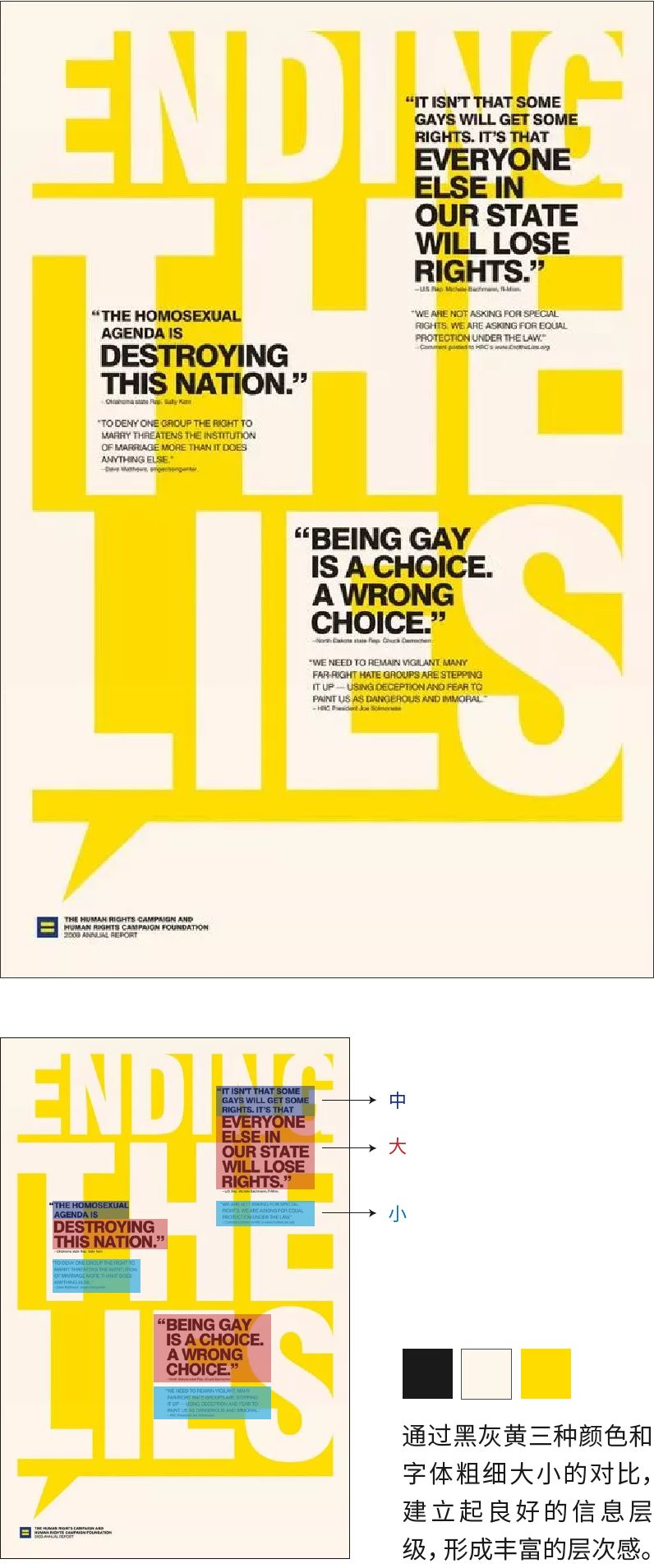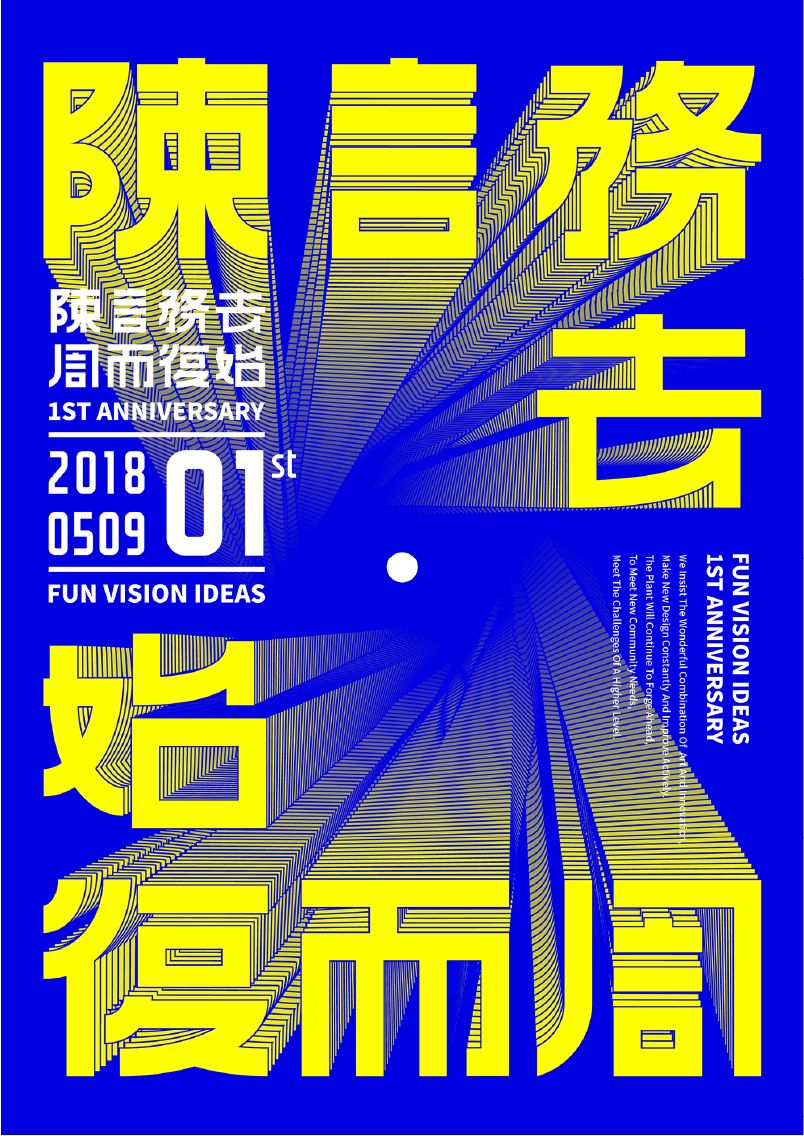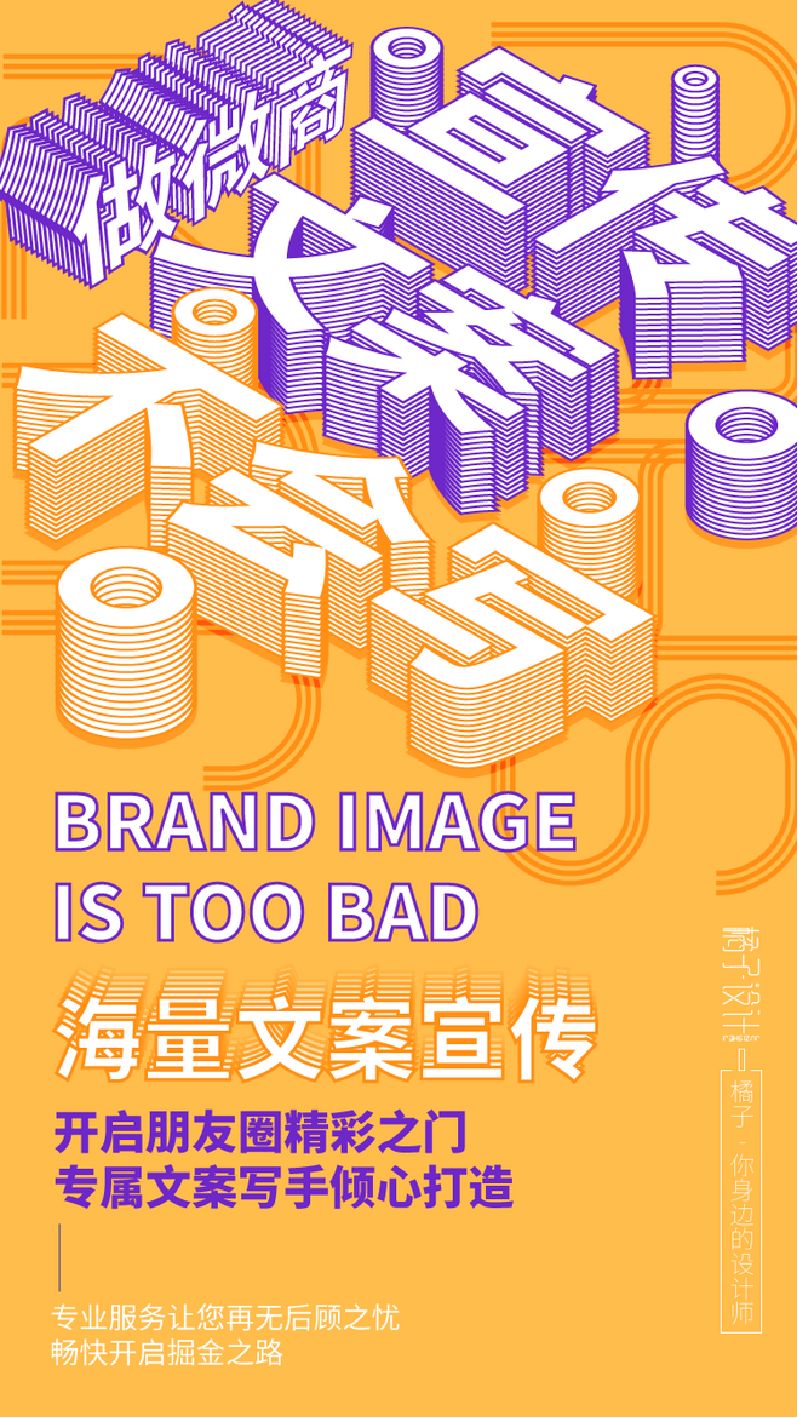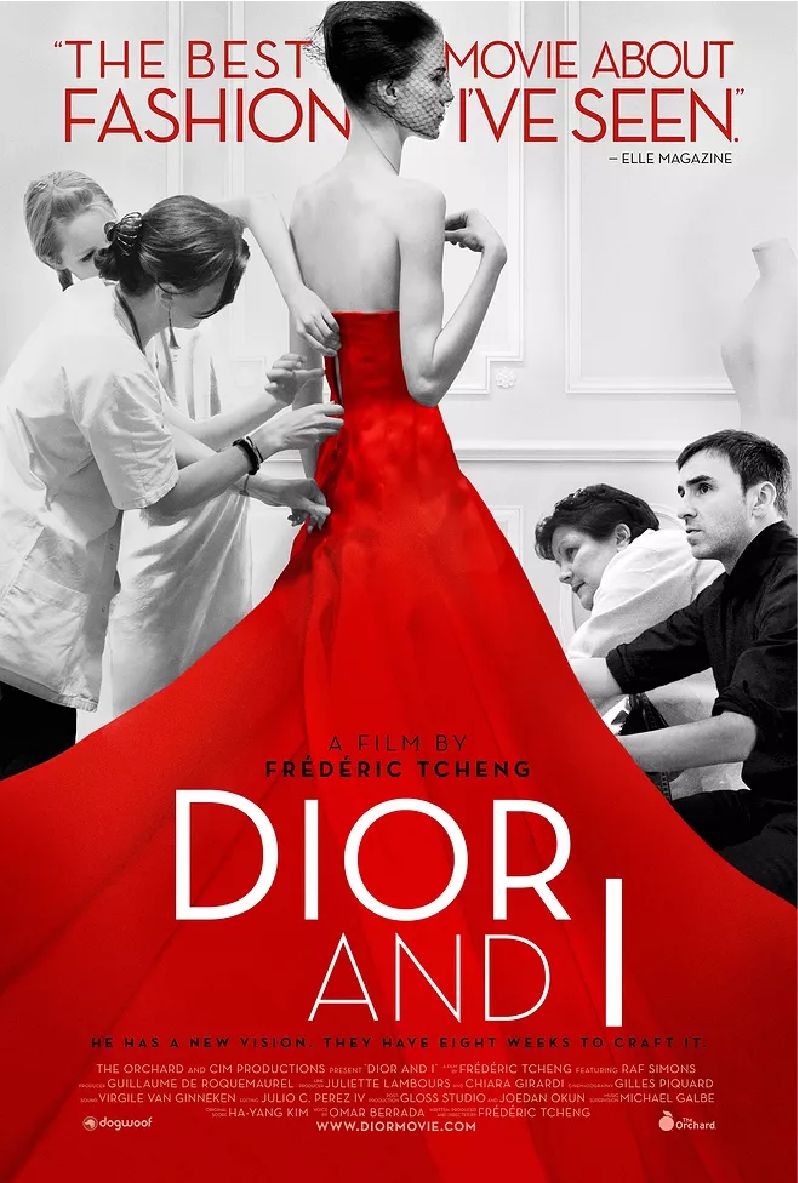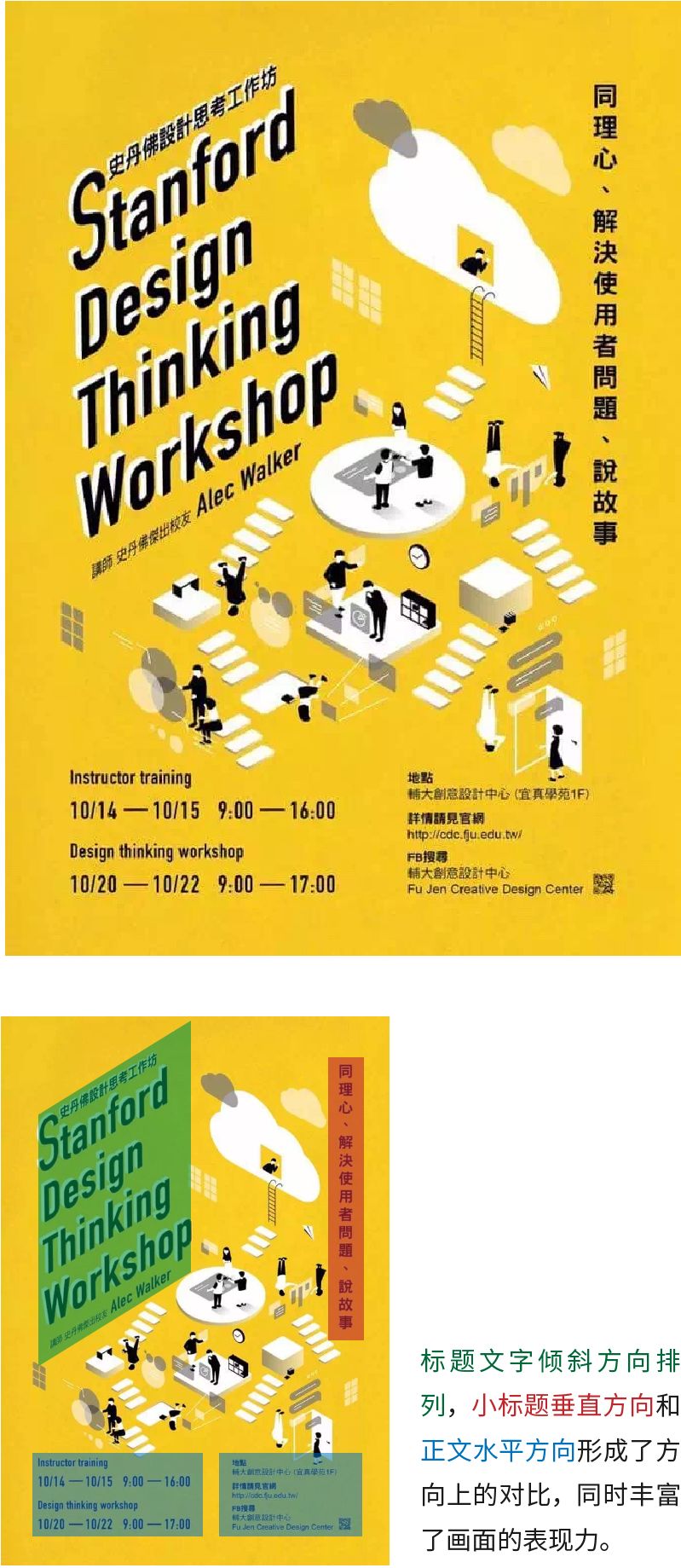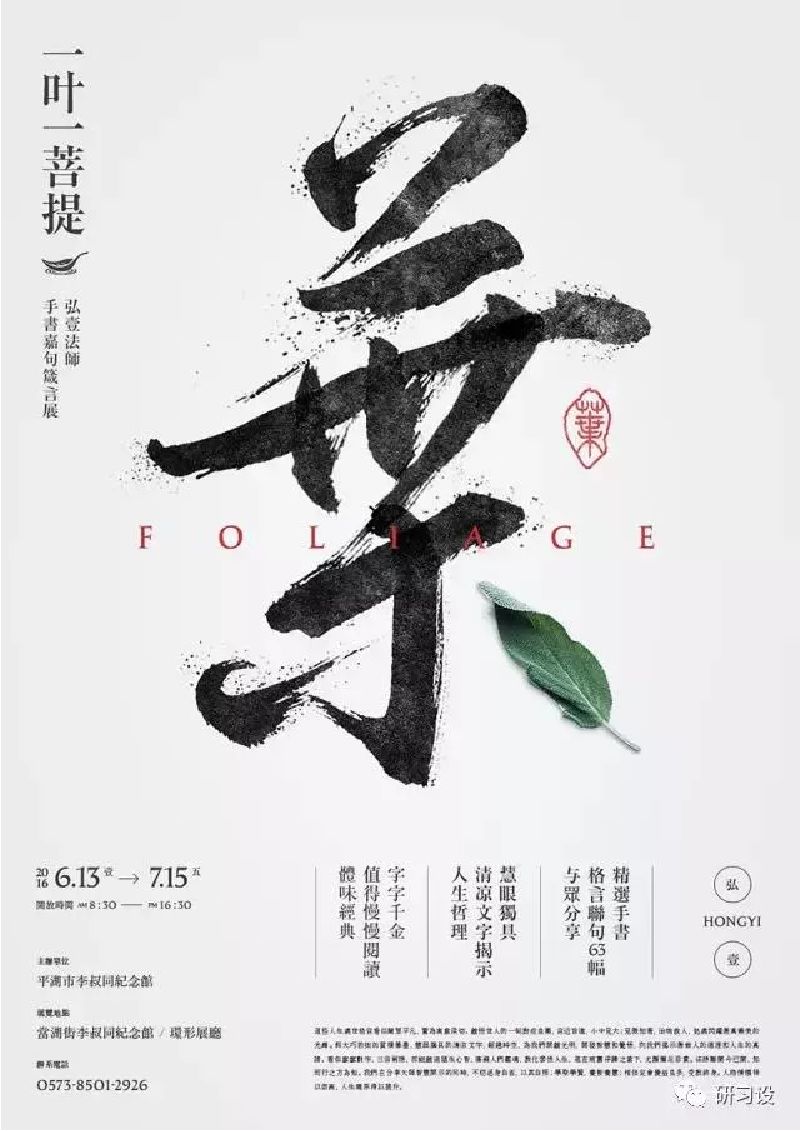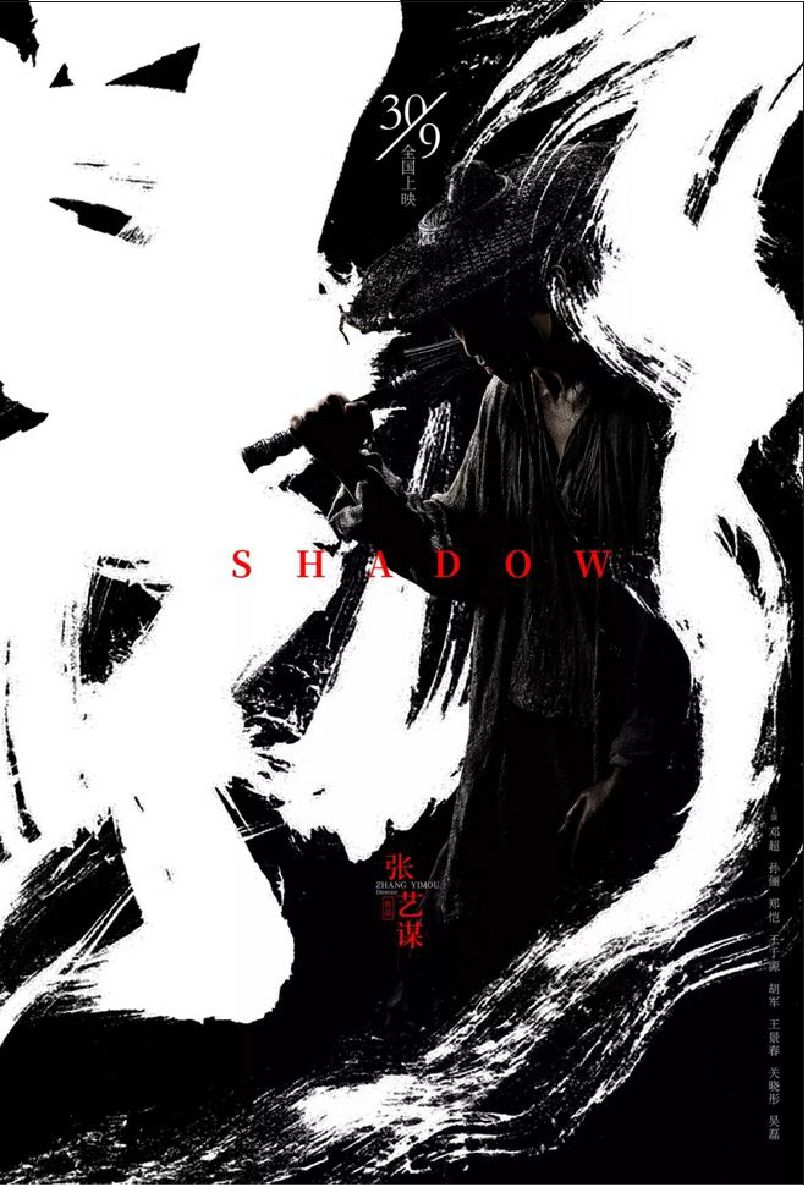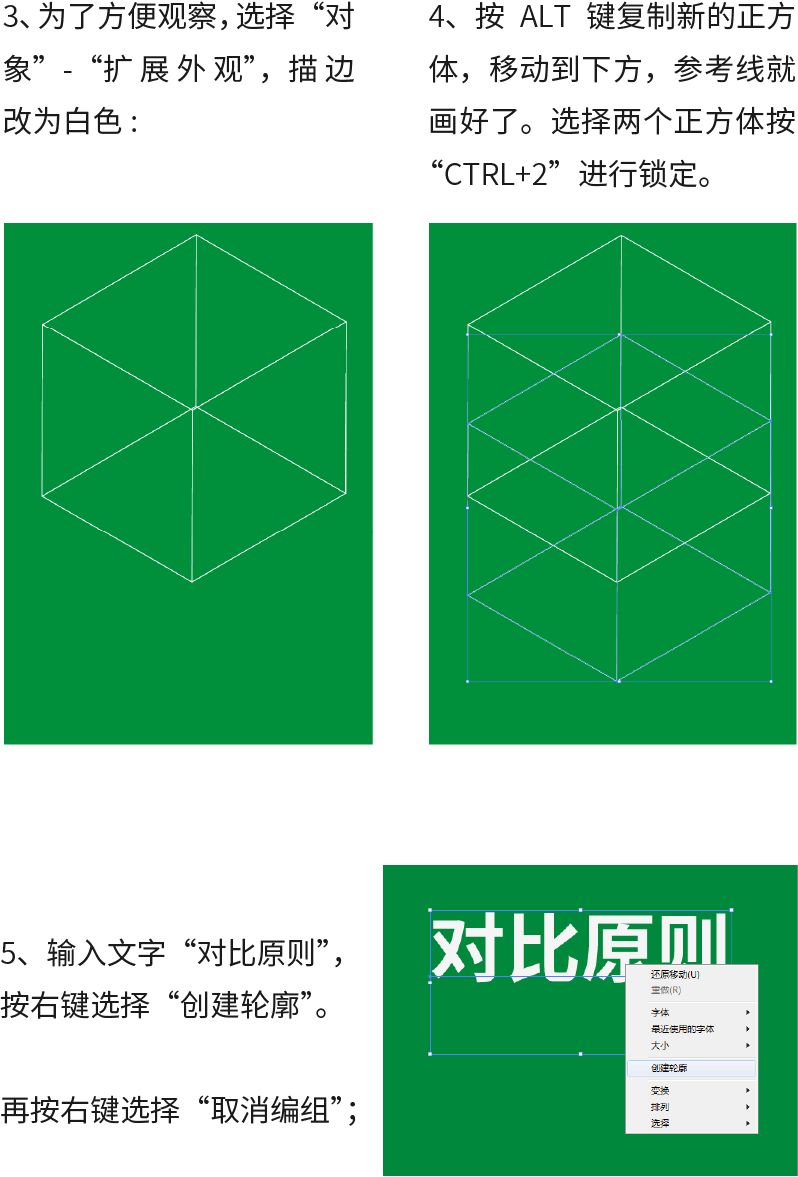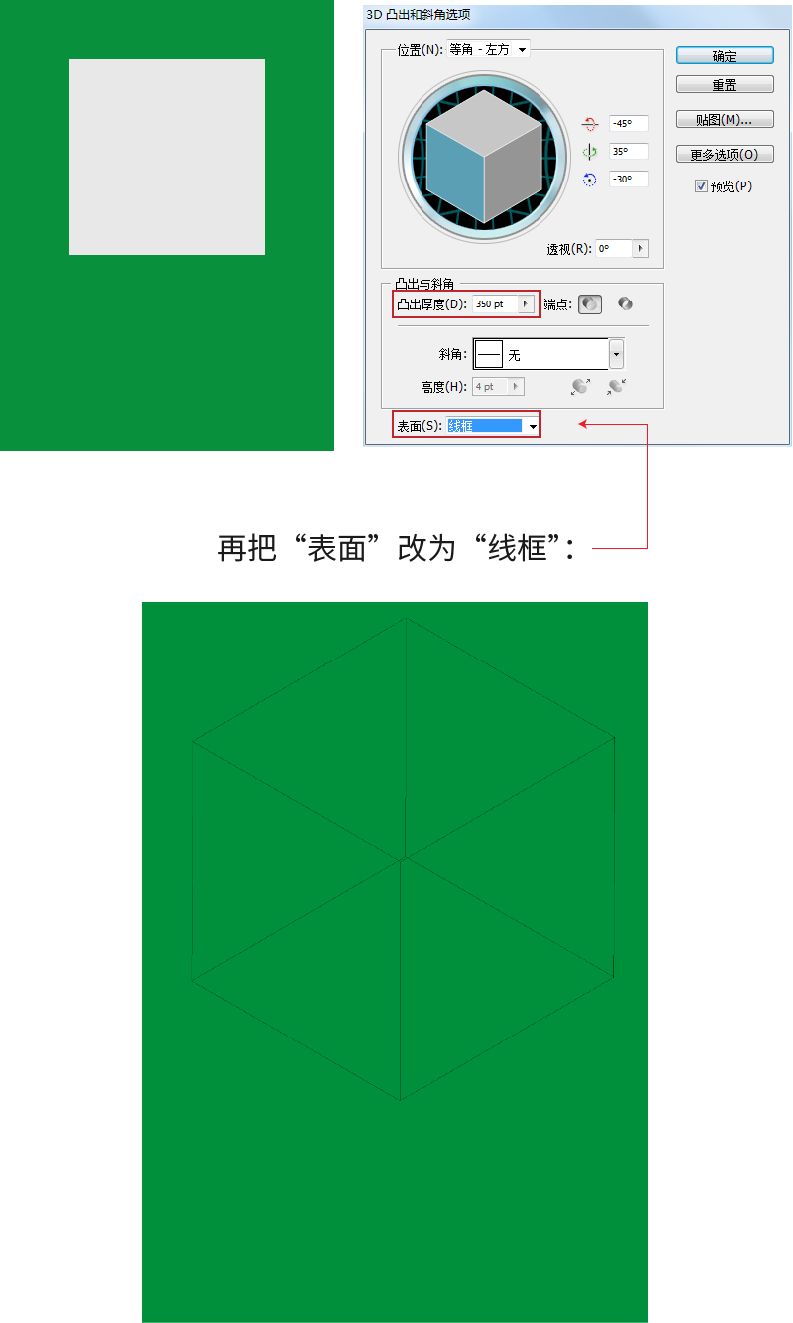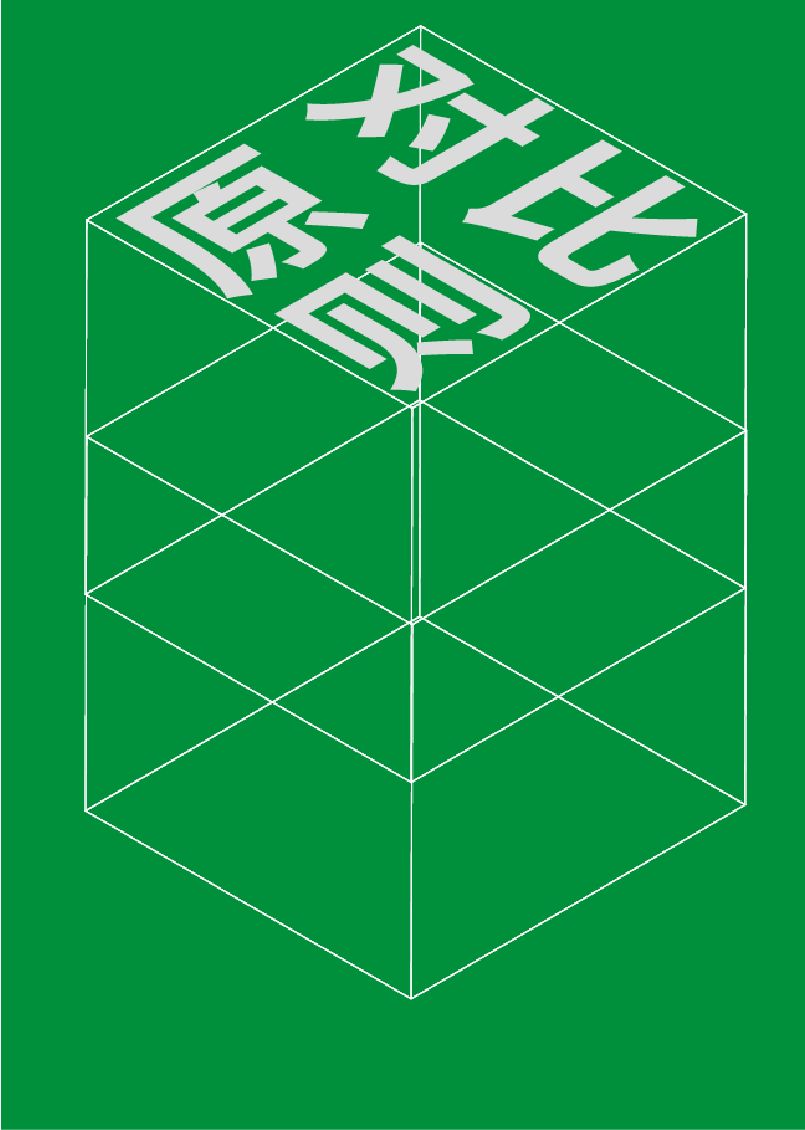
画面太“平”?教你用对比原则解决
重复、对比、对齐以及亲密性是版式设计中的四大原则,各种排版形式与规则都是基于这四大原则衍生而来,而掌握这些具有指导性的设计原则,能够帮助我们在短时间内,更快更好的达成设计目标。本期给大家讲解四大原则之——对比原则。
“对比”强调事物之间的差异性,在设计时要避免页面上的视觉元素太过相似,如果元素之间是为了有所不同,那么加大反差,确保对比是明显并且清晰的。在生活中我们可以随处发现对比的存在,对比形式也是多种多样的:
人们习惯了生活中的对比,如果画面没有对比,会让人感觉很单调乏味。对比可以突出重点,使版面具有层次感,内容要点展示更有条理,对比关系越清晰,视觉效果越强烈。有了对比, 画面才会生动活泼、主次分明。
突出重点
恰当的对比可以很好的制造出焦点(画面主体),在版式编排中,有效利用视觉差异,通过构成要素之间的对比,把读者的注意力吸引到画面的主体部分上来,提高版面的注目效果,是版式设计的重中之重。
利用鲜明的对比,可以形成强有力的反差效果,能第一时间让读者捕捉到主体和重点。此案例主要采用了色彩对比,主体人物和文字在版面中都异常显眼,因为它相比周围的视觉元素产生了很强的差异性。
丰富画面层次
对比是为版面建立有组织的层次结构最有效的方法。强烈的对比可以形成视觉落差,建立良好的信息层次,增强版面的节奏和明快感。
打破呆板、活泼生动
通过对比的形式可以避免版面的单调与平淡,使版面更富趣味性,也使得版面更加鲜活、生动,产生良好的视觉体验,激发读者阅读和观看的兴趣。
用方向、大小和色彩形成对比,使标题与正文的层级更清晰明了,同时加入肌理对比为主体打造立体感,让版面更活泼,更抓人眼球。
理论上元素的一切可改变特征都是可以形成对比,本期只举例了部分常用的文字编排对比形式。
大小对比
通过放大视觉元素体量之间的差异,来达到制造视觉冲突的效果。视觉元素体量大小上形成了层级的划分,体量越大则层级越高,也就越突出。
在版面需要呈现的信息里一般会有标题、小标题、内文之分,也会有重点信息和非重点信息,把重要的信息放大,次要信息则缩小处理,就形成了大小对比。这样做的好处是可以减少次要信息对重要信息的干扰,使之更容易被接收,大小对比还能使版面的层次更丰富。
粗细对比
粗的字体比较沉重,细的字体比较轻盈,字体粗细变化形成了轻重对比。主体信息可以用较粗的字体,次要信息使用较细的字体,利用这种手法制造视觉流程,引导受众阅读信息。
上一期重复原则案例实操中,只使用了思源黑体一种字体,但是采用不同的字体大小和粗细对比,也可以很好的区分信息主次层级。
字型对比
如果版面里的信息比较多,而只使用一种字体的话,也许会显得单调,用字型进行对比,既能把不同信息区别开来,也能丰富版面。
不同的字体有不同的气质,而字型的对比就是不同气质的碰撞。在进行字型对比的时候也要深层次的考虑:字型的选择是否和主体内容相匹配,字体的风格能形成多大反差等。
色彩对比
运用色彩对比可以有效的突出重点、区分信息,还可以起到装饰画面的作用。
大面积的背景色与少量的主体色形成了很强烈的对比效果,能够第一时间把读者视觉引导到文字信息和主角上。
高明度、高饱和度的黄色主体文字和低明度、高冷的黑色背景形成强烈反差,使版面充满活力,也有效突出了文字信息。
方向对比
把版面中的文字信息分别朝不同的方向排列,可以有效增加版面的动感或者空间感。
疏密对比
将大段的文字密集排版,可以让文字形成块状,视觉上更紧凑。剩下来的大面积可以用来展示画面主题,通过这样的疏密变化不但可以形成好的阅读节奏,也能更强化主题。
肌理对比
肌理是指物体表面的组织纹理结构,不同的材质具有不同的触感和视觉体现。文字或背景添加肌理,运用粗糙与细腻、质朴与华丽、厚重与轻薄等对比,可以增添画面的丰富度和表现力。
主体“叶”书法字有着手写的动感,本身就具有质感,置入水墨的纹理进一步强调了效果。可以很好的区分文字信息的主次关系,也增加了画面的视觉美感和艺术表现力。
动静对比
在版式设计中常把有扩散感或具有流动性的图形或文字的编排称为“动”;而把水平或垂直性强、具有稳定性的图形或文字的编排称为“静”。“动”使整个版面充满活力, 获得更高的注目度,而“静”使版面具有稳定的效果,将两者相结合可以产生一定的空间层次感。
电影海报《影》恣意狂放的反白书法字作为背景具有强烈动感,和主角的静形成鲜明的对比,阴阳与刚柔并济,反映出浓浓的古典中式美学。
空间对比
版式设计并不局限于一个平面上的层次,也可以让元素有一些前后关系。文字与形象之间叠压或前后错落编排,使版面出现层次关系,让版面更生动活泼。
虚实对比也可以营造出空间层次,使用虚化的背景来突出前景,不仅能突出重点信息,而且能够较好营造氛围感、场景感和立体感。
使用远近对比体现空间关系,根据透视原理,近则大,远则小,可以营造出近景、中景、远景的画面层次感。
为了让大家加深对“对比原则”的理解,提取本期文章的主要内容做为原始资料,运用“对比原则”进行设计示范。
运用“亲密性原则”进行信息的分组和距离的调整;排版时要遵循“对齐原则”;运用“对比原则”进行信息层级主次的划分,加入文字大小、粗细对比;运用“重复原则”把同一级别的文字设置为相同的文字样式,增加条理性,加强统一性。
为了使对比更丰富,可以加入字型和色彩对比,加强层级关系,使重点内容强调突出。
现在画面文字信息已经清晰而有序的排列好,但是缺少主体。把标题内容“对比原则”作为主体元素的进行设计。
1.打开AI软件,画出一个正方形;
2执行“效果-3D-凸出和斜角”。勾选“预览”,“位置”使用“等角-左方”,“凸出厚度”可以自己调整使正方形变为正方体。
6、分别给四个字执行“效果-3D-凸出和斜角”,把“位置”改为“等角-上方”,厚度改为0:
7、把文字填充色改为白色,描边改为背景色绿色,按照参考线去摆放文字的位置,把“原则”两字逆时针旋转90度放置;
8、选择四个字,右键选择“编组”,
复制两组新的文字,一组备用,一组放置到下方。
9、选择上方的文字组,右键“排列-置于顶层”;
在工具栏选择“混合工具”,分别点击两个文字组,再双击“混合工具”调出“混合选项”,间距选择“指定的步数”、“30”;
10、把之前复制出来备用的文字组填充绿色,右键选择“排列-置于顶层”,再移动到原文字组位置;
11、英文按照同样的方法设计好放在下方,主体就刻画好了;
12、按“Ctrl+Alt+2”键解锁全部对象,删除参考线。
把之前刻画好的文字信息排列在画面下方,严格按照对齐原则进行排列,主体图形与文字信息形成了方向对比和肌理对比,视觉效果也更丰富。
观察画面整体效果,发现宋体字与版面中的风格不统一,所以去掉字型对比,把所有文字统一修改为思源黑体;尝试把色彩对比也取消,版面视觉效果更简洁纯粹。设计完成:
重新尝试使用其它对比手法设计新方案。把“对比原则”四字放大并错落的放置在版面中,形成位置上的对比。
把之前刻画好的文字信息放置在画面中,整体文字排版采取两端对齐的形式,但在局部采用左对齐和右对齐形式,形成排版方向上的对比。
加入英文丰富画面,排版方向改为纵向排列,这样增加了方向对比;给背景加入点状肌理,形成肌理对比。
为使对比效果更丰富,把“对比原则”四字执行“效果-模糊-径向模糊”,形成动静对比和空间对比,设计完成:
总 结
1、对比可以突出重点,使版面具有层次感,内容要点展示更有条理,有了对比,画面才会生动活泼、主次分明;
2、理论上元素的一切可改变特征都是可以形成对比,本期只举例了部分常用的文字编排对比形式;
3、通常一个作品中不会只使用一种对比,而是多种对比方式组合使用。对比关系越清晰,视觉效果越强烈。但要根据版面内容选择合适的对比手法,强调对比时,要注意画面的和谐统一。